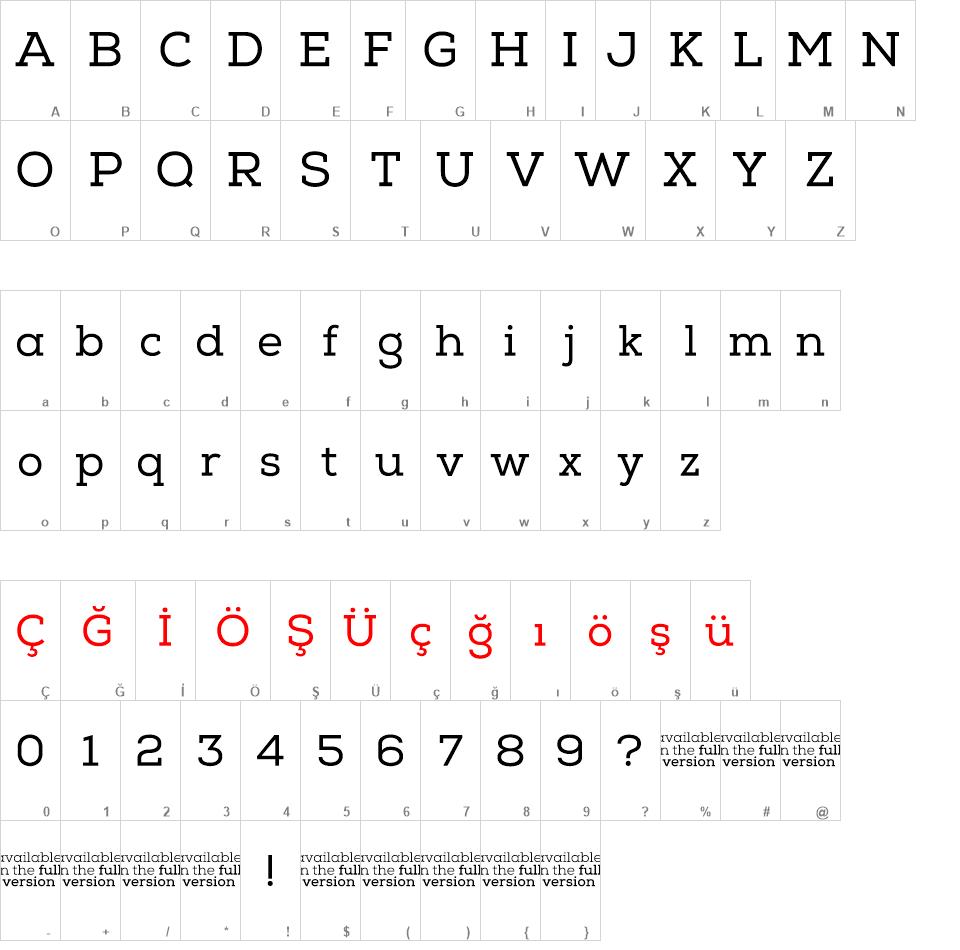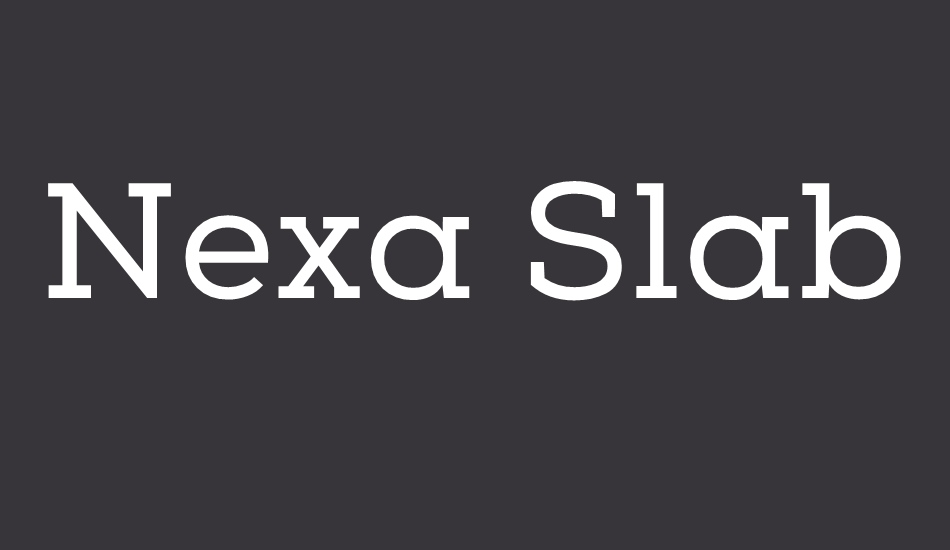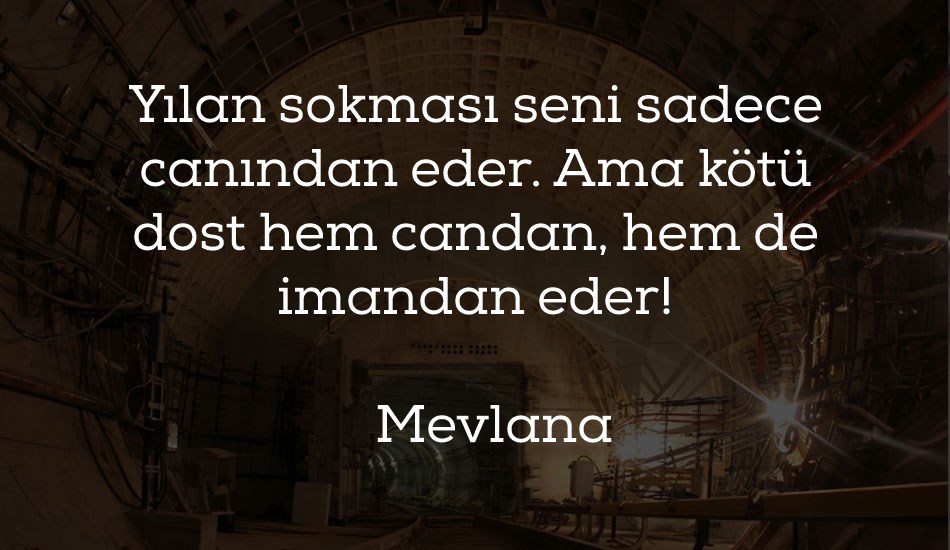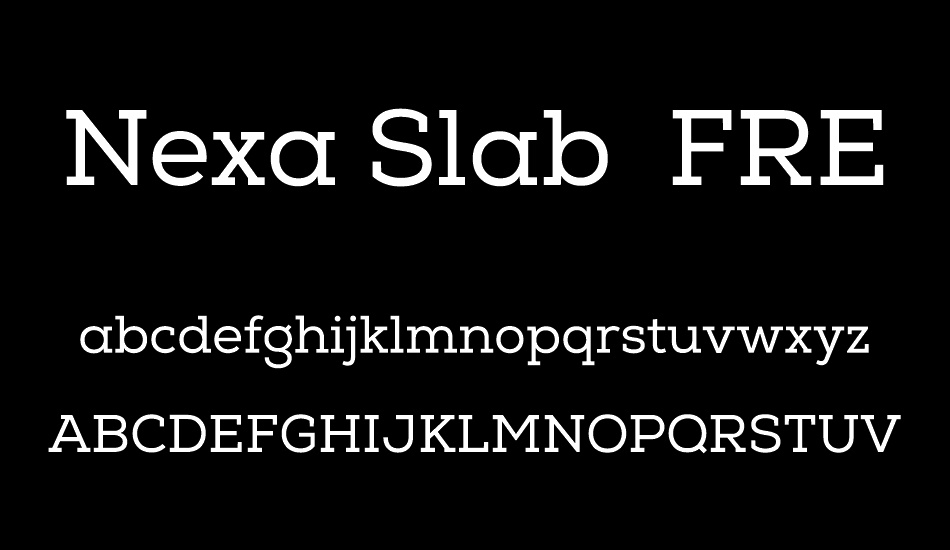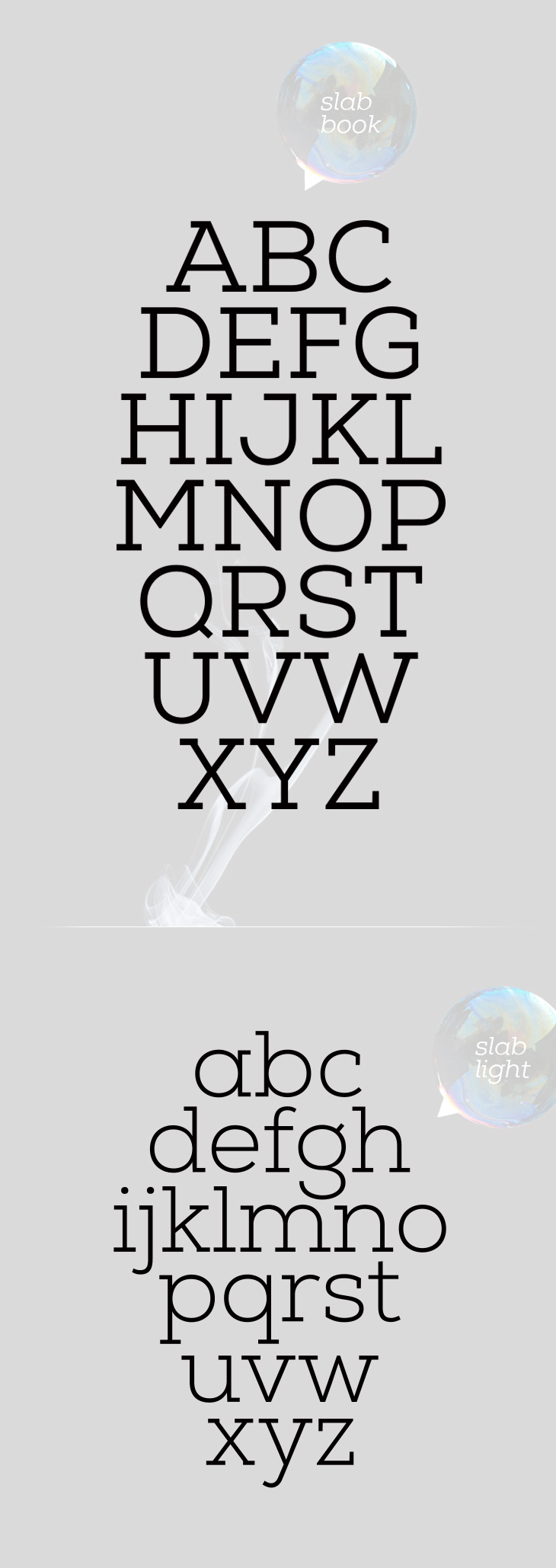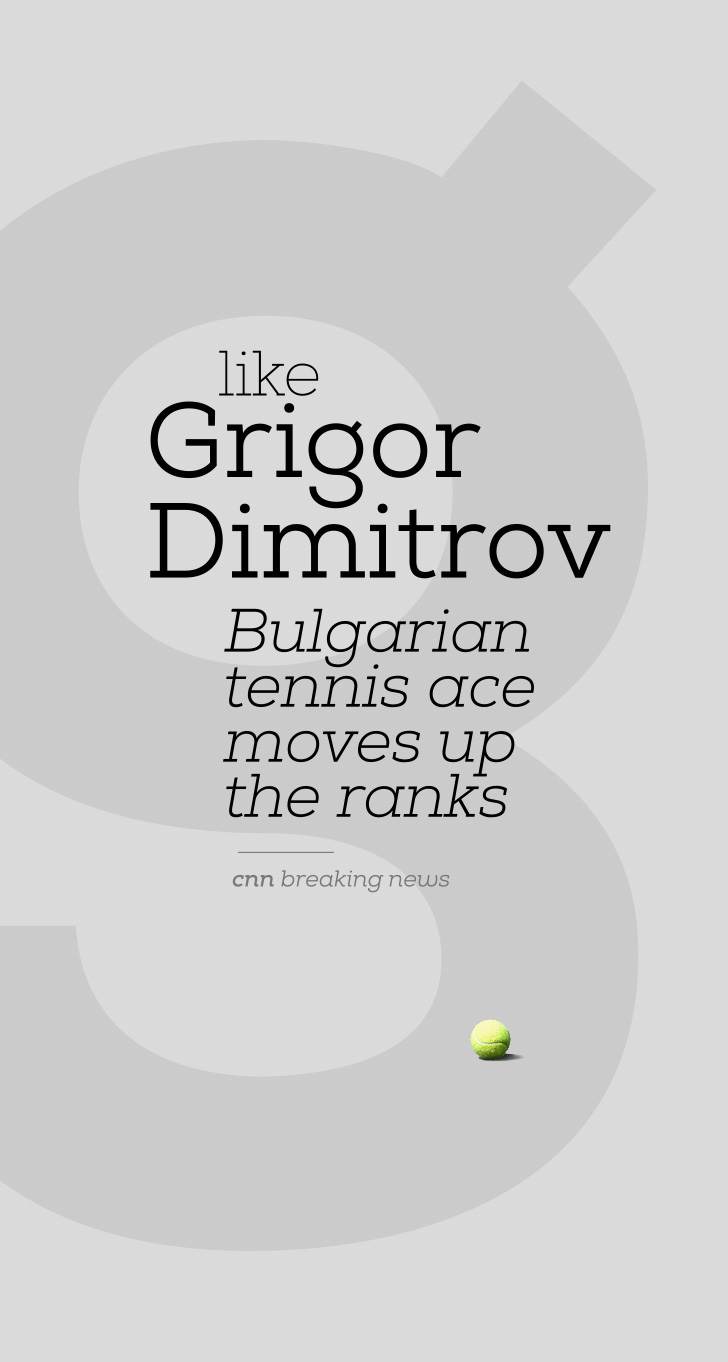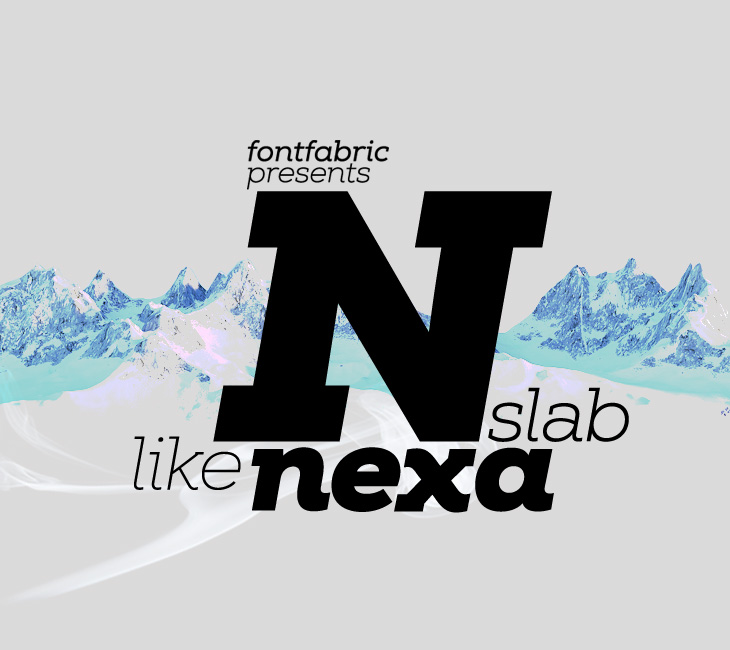
Nexa Slab font
Yazı tipi ailesi 3 temel form içerir: eğik çizgi, eğik çizgi ve dikey çizgiler, bunların her biri 8 farklı gramaja sahiptir. Bu görsel zenginlik, web için ideal kütük serif yazı tipi ailesi, ayrıca baskı, hareketli grafikler, logolar, tişörtler ve benzerleri. Başlıklar için harika, hem küçük hem de büyük dizgi metin bloklarıyla uyumlu.
Nexa Slab, önemli reklamcılık işlevinde metnin zenginliğini gizleyen Lubalin Graph, Rockwell ve Memphis gibi klasik Neo-Grotesk slab serif yazı tiplerinin zengin geleneklerini çizer. Tıpkı bu yazı tipleri gibi, tasarım rasyonel, özenle düşünülmüş, kalın ve ince çubuklara ve aralarında düşük bir kontrasta tabidir. Harflerin orijinalinin sıkı geometri ve kare oranları, uygun şekilde dengelenmiş kütük seriflerle ekstra kuvvetlendirilmesi ile karakterizedir.
Nexa Slab sert, esnek olmayan, bitmiş ve hiç eksik olmayan, monoton olmadan sistematik olan ciddi bir durumdur ve ilk bakışta kısa, doğrudan mesajlar için daha uygun görünse de; Bir usta tasarımcının elinde ... enfes ve ahenkli tasarımlar inşa edebilir ve yaratabilir.
Nexa Slab Regular FREE font